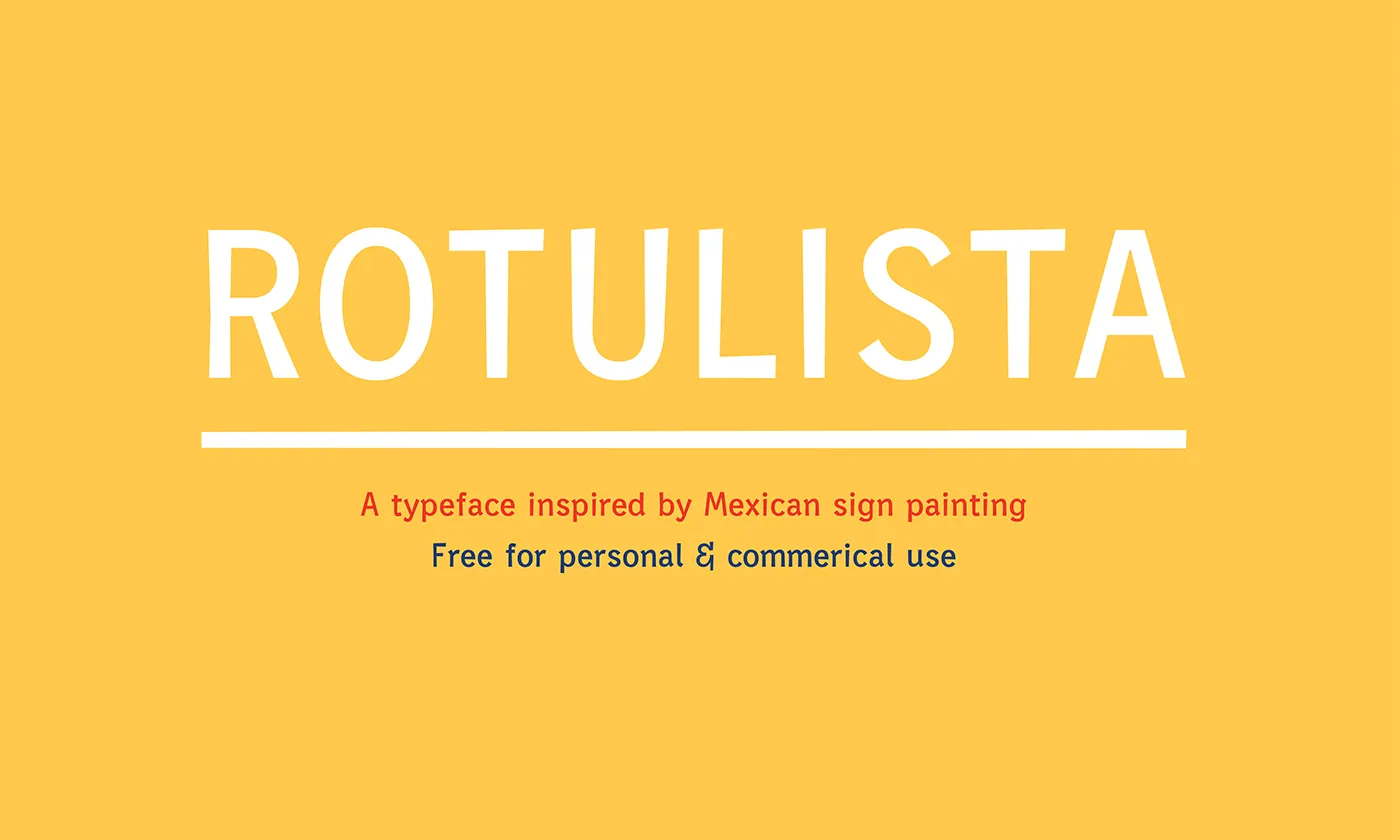
Rotulista Typeface – Download Grátis
Introduzimos Rotulista Typeface. Desenvolvida e compartilhada por Sam Bumbalo, um designer nascido na Kent, Ohio, nos Estados Unidos, Rotulista é uma tipografia inspirada no pintar de sinais mexicano. Inspirado em uma cultura vibrante e colorida, Rotulista possui uma estrutura limpa e fluida que transmite força e flexibilidade, mantendo seu tom amigável e alegre. Ideal para headlines, corpo do texto e cartazes de protesto; Rotulista tem como missão capturar o espírito americano – a esperança, não a intolerância. Convidamos você a explorar sua versatilidade em criações digitais, seja um website dinâmico ou uma publicação online. Suas linhas arredondadas e seu design limpo podem transformar qualquer design digital em algo mais poderoso e vibrante. Rotulista é uma escolha ideal para quem busca uma fonte de sans-serif que possa destacar sua mensagem de maneira elegante, sem perder o contato pessoal e alegre característico da tipografia. Seja no seu blog, site ou redes sociais, Rotulista está lá para ajudá-lo a comunicar suas ideias de forma impactante.